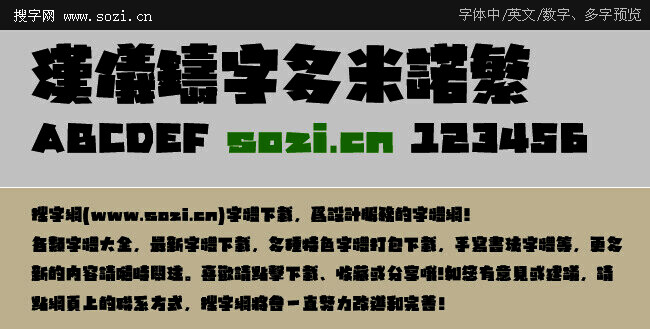
漢儀鑄字多米諾繁
搜字網(wǎng)給大家提供一款漢儀鑄字多米諾繁中文字體下載,漢儀鑄字多米諾是一套廣告POP字體,字體筆觸鮮明,字形夸張醒目,筆畫可愛灑脫,結(jié)構(gòu)充滿變化,非常有趣味性。適用于畫冊(cè)設(shè)計(jì)、海報(bào)設(shè)計(jì)、包裝設(shè)計(jì)等場(chǎng)合使用。(本字體為個(gè)人非商用版,如需要商用請(qǐng)聯(lián)系漢儀公司購(gòu)買版權(quán))